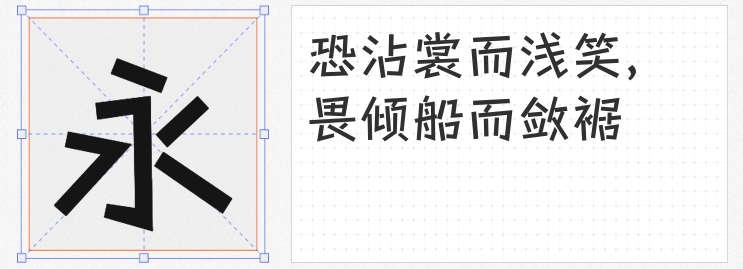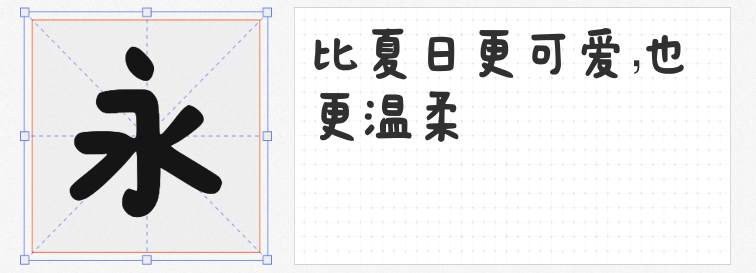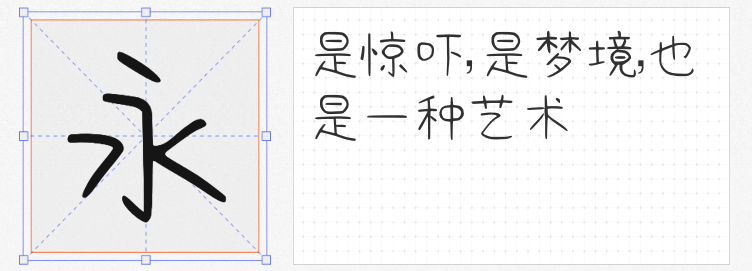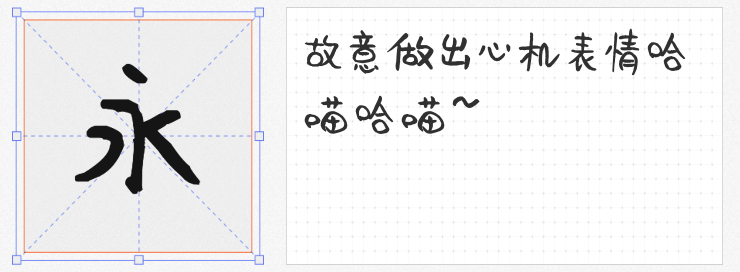
在追求视觉趣味的平面设计领域,可爱风格字体以其温暖治愈的特质,成为品牌IP、儿童产品、社交媒体等场景的“吸睛利器”。以下四款免费商用字体,兼具萌系美学与实用价值,助你轻松打造令人心动的视觉作品。
1. 字体家AI造字春风
由AI算法生成的这款字体,以圆润饱满的笔画勾勒出童话般的氛围。每个字符仿佛自带“呼吸感”,转折处如气球般轻盈上扬,卡通化设计完美适配儿童绘本、节日海报等场景。其无拘无束的创意形态,让文字本身即成为画面中的趣味元素。
2. 礼品卉自由理想体
这款字体将“松弛感”发挥到极致:横竖笔画故意保留手写时的微妙倾斜,框形结构被俏皮的圆圈替代,宛如慵懒午后蜷缩在沙发上的猫咪。这种不刻意的“不完美”,反而营造出亲切随性的视觉语言,尤其适合文创产品、生活类品牌宣传。
3. 平方萌萌哒
横画如波浪般自然起伏,字间距透着孩童涂鸦的天真感。这款字体巧妙平衡了规整与灵动,既保留手写体的温度,又通过适度夸张的笔画弧度传递萌趣气质。无论是社交媒体表情包设计,还是幼儿教育类PPT排版,都能瞬间拉近与受众的距离。
4. 游趣体
以日文字体为灵感,这款字体将所有笔画简化为纤细直线,却在转折处暗藏玄机:类似麦穗的短促顿笔,赋予文字田园诗般的清新气质。看似简约的设计中,通过独特设计展现的的连笔变化,让文字在静态中蕴含动态韵律,适合自然主题包装、手账素材等场景。
这四款字体以不同方式诠释可爱美学,从AI科技的未来感到手写温度的人文关怀,从慵懒随性的生活哲学到田园牧歌的诗意想象,为设计师提供了丰富的创意工具箱。更难得的是,它们均支持免费商用,让萌系设计不再受限于预算壁垒。